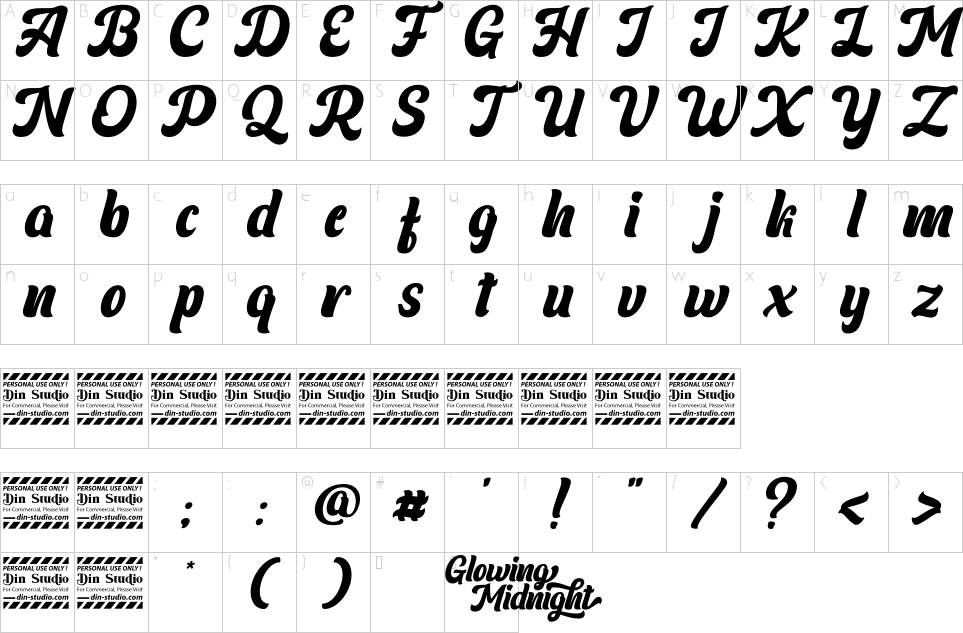
Descubra a beleza sofisticada da fonte Glowing Midnight, perfeita para tornar seus projetos ainda mais criativos. Desenvolvida pelo designer Natha Type, essa fonte oferece uma iluminação mágica e única, ideal para design de logos, gráficos, e até mesmo para gravação de letras em vídeos. Conforme descreve a descrição original, Glowing Midnight foi uma escolha popular, sendo baixada por 6.989 pessoas, o que demonstra o seu valor e desempenho. Essa fonte é perfeita para designers que procuram um tom elegante e luminoso para suas criações. A Glowing Midnight é perfeita para quem busca uma fonte única e moderna para dar vida a seus projetos digitais. Seja para criar designs de marca, texturas de gráficos ou mesmo para adicionar um toque especial em sua próxima transição de texto no vídeo, Glowing Midnight será uma escolha inteligente.